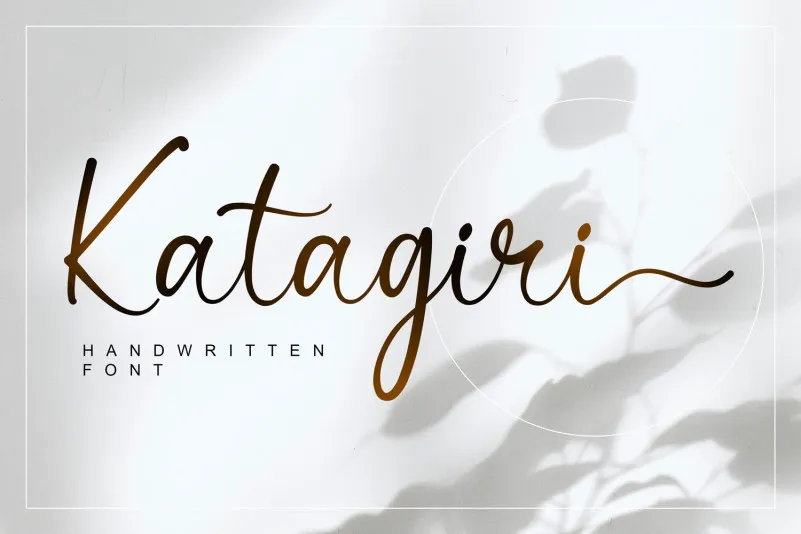
Katagiri é uma linda fonte script que surgiu no lemeThe, criada para quem busca elegância e sofisticação em suas criações digitais. Esta fonte está pronta para uso, com detalhes meticulosos e perfeitamente codificados PUA, o que significa que você pode acessar todos os caracteres e swashes sem qualquer dificuldade. Com um fluxo suave e delicado, ela irá levantar cada projeto design em que você desejar criar. É uma fonte perfeita para uma variedade de aplicativos, incluindo convites de casamento, material de estação, fotografia, postagens nas redes sociais, embalagem de produtos, cartões de cumprimento e muito mais. Katagiri é a escolha ideal para quem deseja dar um toque especial a seus trabalhos digitais, elevando-os ao próximo nível de qualidade e elegância.